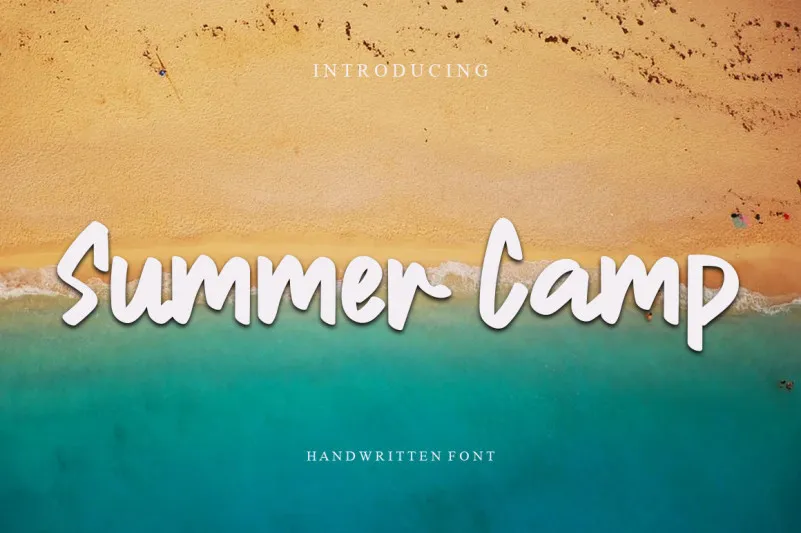
Summer Camp Script Font – Download Grátis
Esta é uma fonte escrita à mão única, divertida e amigável para quem quer dar vida a suas ideias criativas. Seja para marcar presença no Instagram ou adicionar um toque de artesanato à sua próxima peça de decoração caseira, essa fonte transformará seu projeto em uma obra de arte verdadeira! Com o Summer Camp Script Font, os desenhos e as ilustrações ganham vida ao estilo do papel de convite para festa da infância. Estando disponível tanto para redes sociais quanto para projetos DIY, você encontrará uma fonte que irá tornar suas criações ainda mais atraentes e inovadoras. Navegar pela web ou mesmo criar um desenho pelo seu próprio tempo se tornará uma experiência divertida graças à versatilidade desta fonte criativa e encantadora.